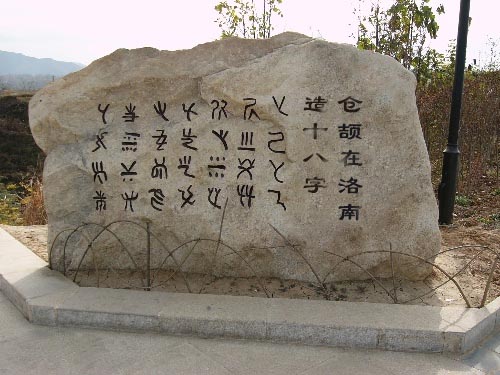
仓颉造字
仓颉是谁?仓颉是中国汉字的创造者,中国历代文人,都把他尊奉为文祖。据说仓颉出生在陕西白水县,现在白水县还有国内唯一一座纪念仓圣造字的庙宇——仓颉庙。
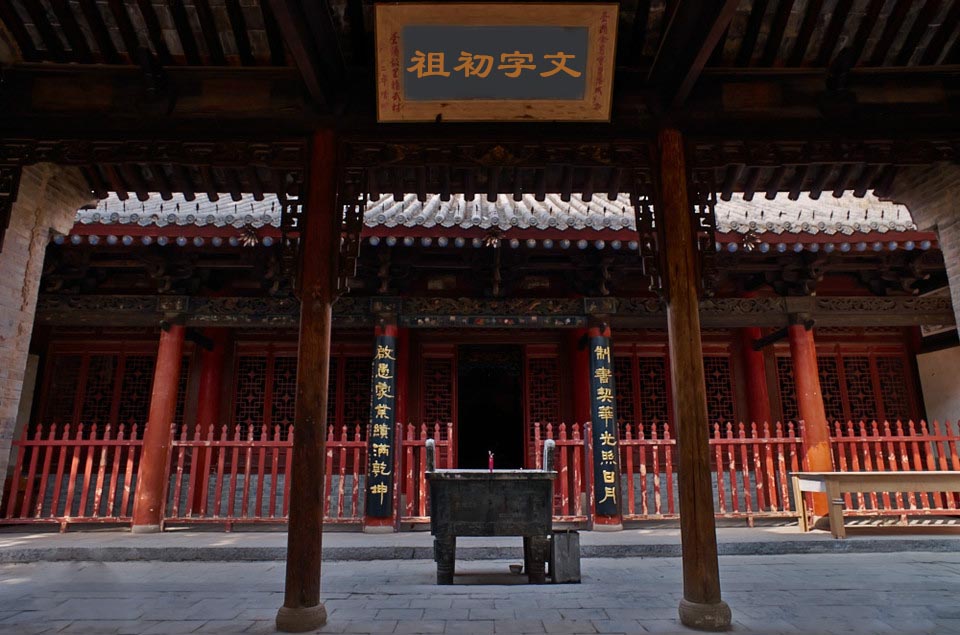
仓颉,据传说复姓侯冈,又名史皇氏,双瞳四个眼睛炯炯放光,观察力超强,总结概括是一把好手,抽象思维更是无人能及。公元前2685年,黄帝打败蚩尤,统一了华夏大地,因为仓颉多才,黄帝任命他为史官。
黄帝当首领的时候,中国还处于新石器时代,记事采用的是结绳法,可要记的事项多了,这种方法就不好使了。而且要解开绳结也比较麻烦,于是他又发明了画图法,用石头在地上画图,但画图麻烦不说,也没有那么多可保存图的地面,如果画在外面,一场大雨下来,就什么都没有了,因此,仓颉只好另觅他法。
有一天,仓颉在一个岔道口遇到了三个猎人,猎人正在争论,去追踪哪种猎物好,他很奇怪地凑过去,一问之下才知道,原来他们是通过鸟兽的足迹,正在判断逃走的猎物,地上清晰的足迹,就像一个个笔画,给仓颉带来了启发,于是他就用那样的笔画,根据物品的形状,创造了像形文字。这可是一项惊天地泣鬼神的大发明大创造,文字的出现,使华夏文明一直繁荣昌盛到今天。
仓颉的形象,随着时间的推移,变得越来越神化了。在战国晚期儒家大思想家荀子的著作中,荀子非常理性的推断:"好书者众矣,而仓颉独传者壹也"。意思是说,文字的出现,绝不可能是一个人在一段时间内发明创造出来的,它必然经历过无数人的探索,经过很长一段历史时期的打磨与积淀。而仓颉是在前人的基础上,加以总结、完善、修改和系统集成,进一步优化而形成的文字。
这应该更接近历史的真相。